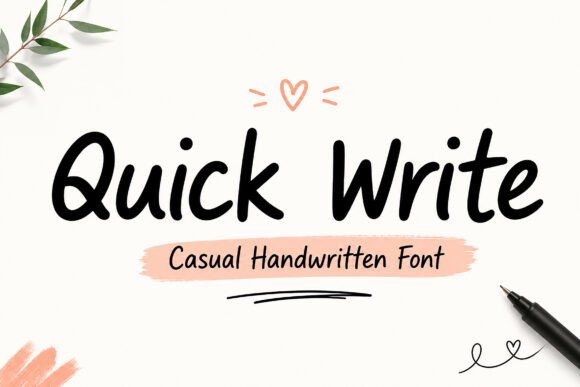
Quick Write
Если вы ищете высококачественные ресурсы, такие как Quick Write, этот премиум-пакет — фантастический выбор для ваших творческих проектов.
Создаете ли вы продукты POD (печать по требованию), свадебные приглашения или графику для социальных сетей, Quick Write станет идеальным выбором.